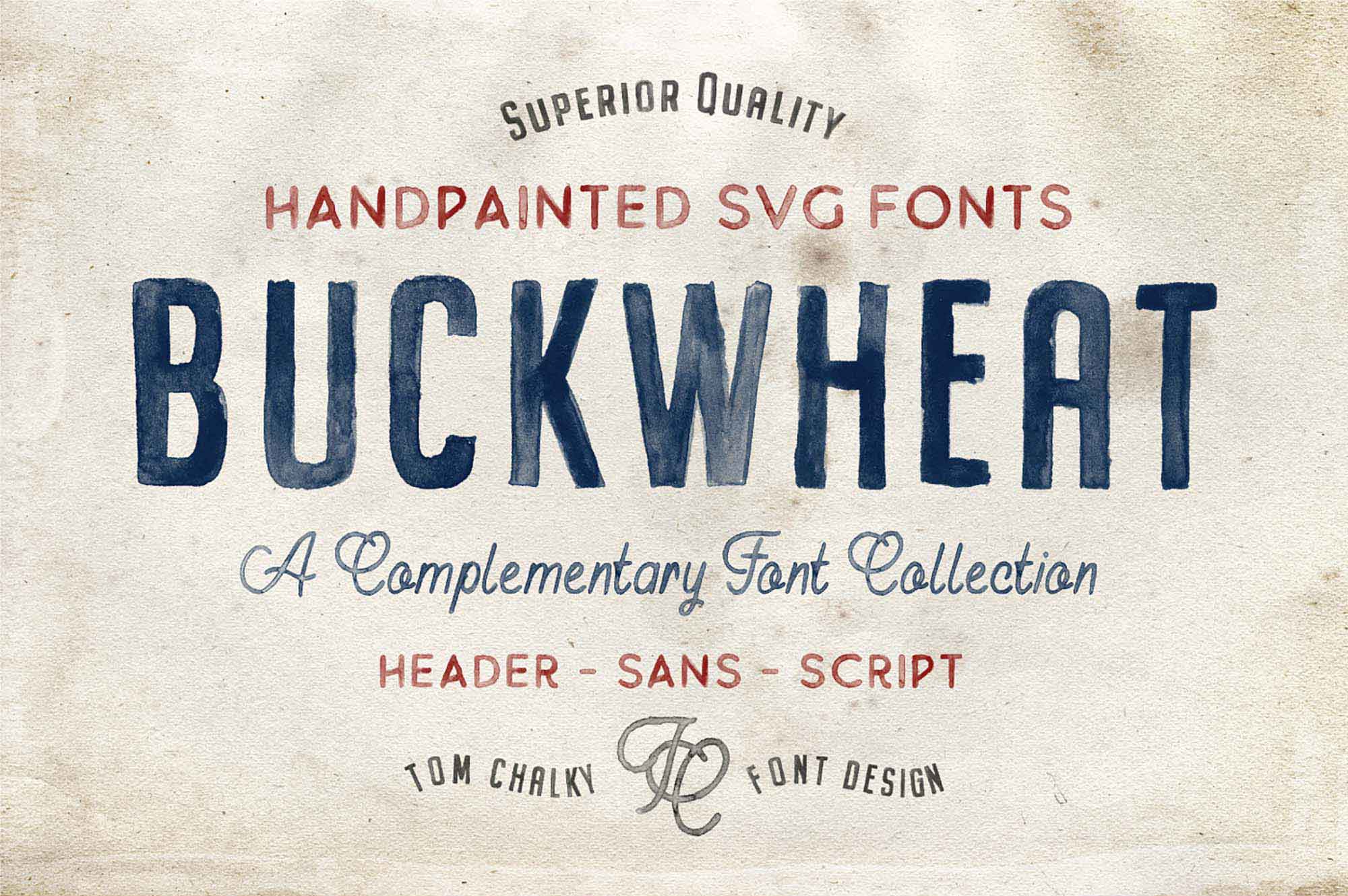
Buckwheat Hand-painted Font (SVG)
Aqui está uma descrição em português para a página de download do recurso gráfico ‘Buckwheat Hand-painted Font (SVG)’: Tom Chalky criou mais um trabalho de arte inspirado, agora com uma fonte de letra pintada a mão. Esta criação vem num formato SVG, uma das formas de representar designs gráficos que é extremamente flexível e suave. Com uma variedade de detalhes cuidadosamente pensados para cada letra, cada design da fonte traz a essência da arte à digitalização. Estamos certamente que esta fonte é uma jóia rara para qualquer designer que aprecia a mistura de elementos artísticos e técnicos. O Buckwheat Hand-painted Font (SVG) é uma coleção de recursos gráficos que abraça a essência da personalização, oferecendo aos designers uma maneira singular de dar uma nova identidade a um texto. É essencialmente um tesouro para o seu projeto, permitindo que você personalize a aparência do texto, seja para um logotipo, uma capa de livro ou qualquer outro elemento visual. Seja você um designer gráfico, um artista digital ou um designer de web, certamente vai adorar explorar os muitos recursos que a fonte Buckwheat tem a oferecer.